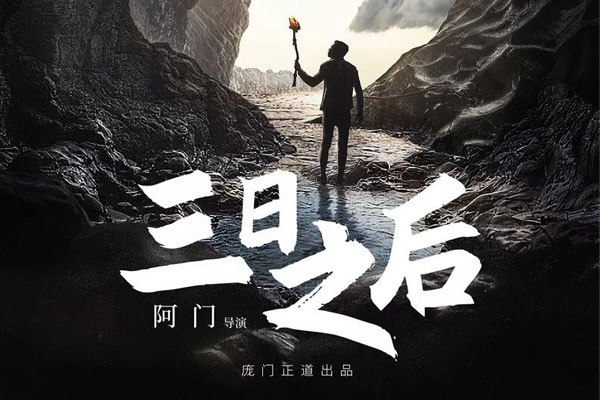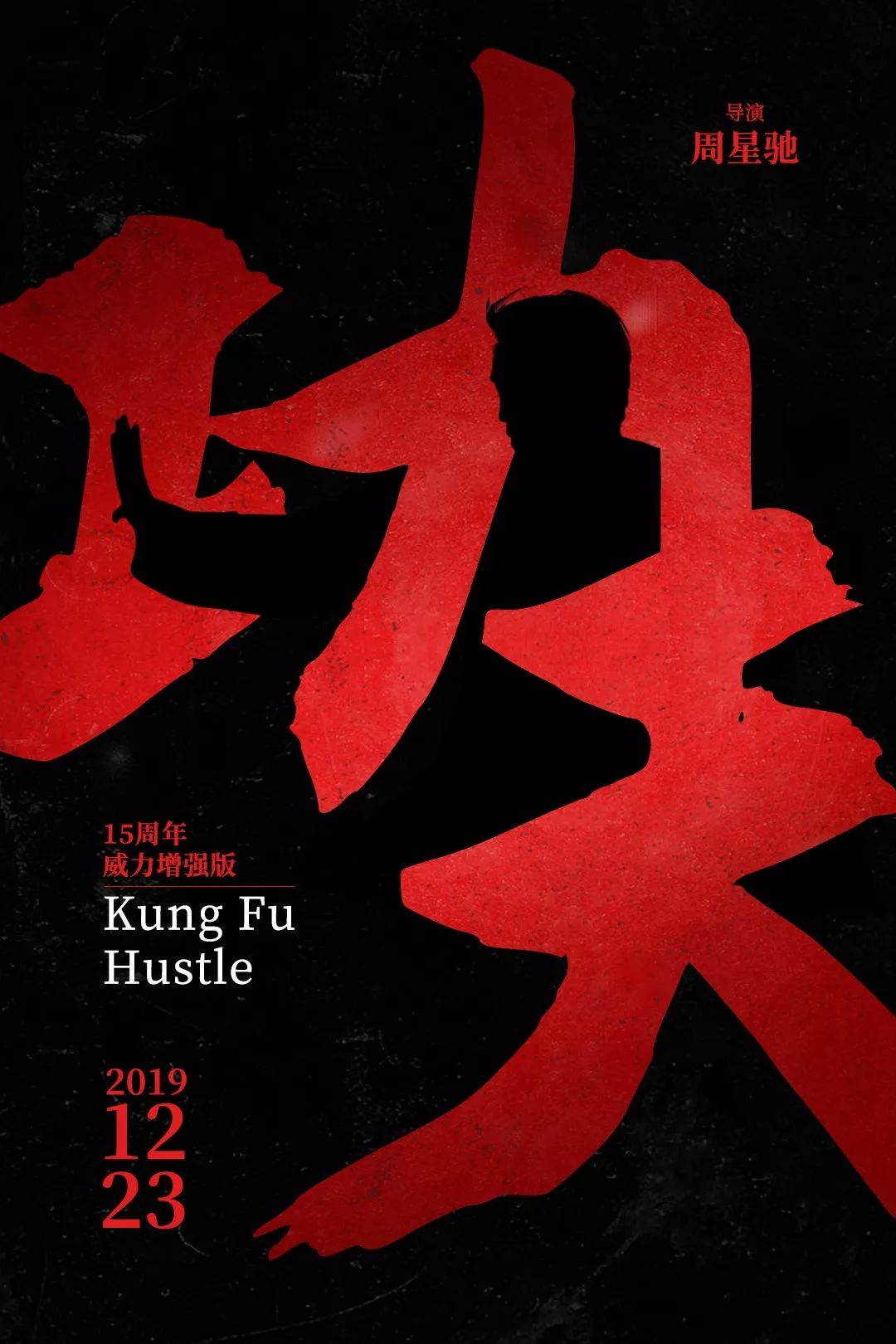
庞门正道粗书体
这款字体是由《庞门正道》设计公众号与设计师车港敏共同研发的,耗时九个月,投入超过15万元。为了帮助大家解决使用字体时的侵权问题,车港敏同学为大家带来了一款更加精美实用的书法字体,而且完全免费商用!不论你是个人还是企业,都可以免费使用这款字体,无需支付任何费用。重要的事情的是:完全免费商用!
庞门正道粗书体效果预览
庞门正道粗书体字体效果预览